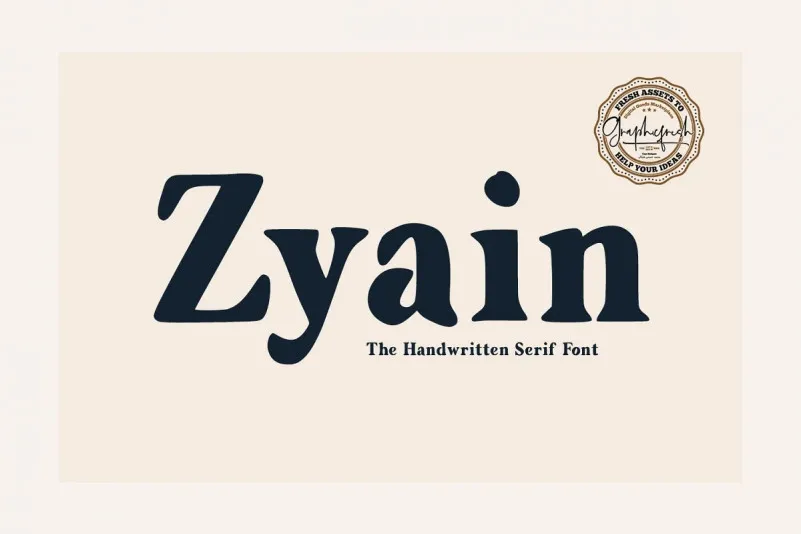
A fonte Zyain é uma elegante tipografia serif que combina elementos vintage e elegantes com uma delicadeza única. Criada pelo talentoso designer Graphicfresh através do site de concursos 99designs, essa font é ideal para destacar qualquer projeto. Seu estilo suave e feminino se destaca em diferentes aplicações gráficas, como a criação de marcas, convites de casamento, revistas, chinelos, cartões de visita, citações, panfletos e muito mais. Ideal tanto para um design minimalista quanto para aqueles que valorizam uma estética mais sofisticada e delicada, o Zyain é certamente uma fonte indispensável no seu arsenal gráfico.